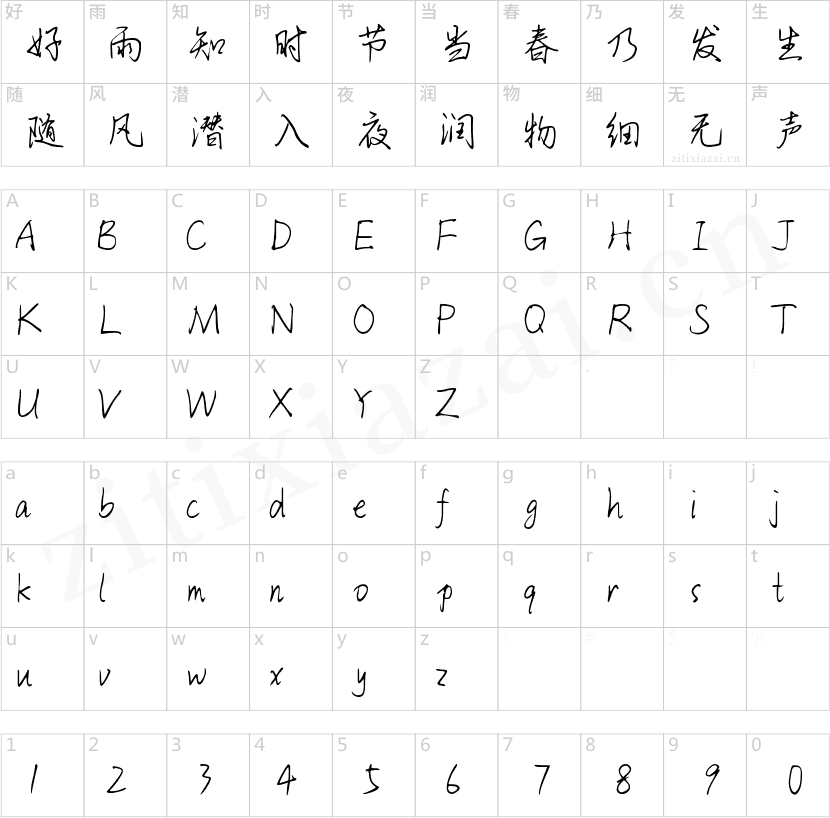
Aa荒城渡
Aa荒城渡字体
Aa荒城渡是一款非常具有艺术性的字体,它的设计灵感来源于对古典艺术的研究,同时又融入了现代字体设计的元素。字形优美,笔画粗细变化自然,给人以大气、典雅的感觉。Aa荒城渡是一款既传统又现代的字体,它的设计充满艺术感,美观大方,实用性也非常强。无论是对于设计师还是对于普通读者来说,都是一种非常不错的字体选择。Aa荒城渡适合用于具有艺术感的场合,比如海报、宣传单张、书籍封面等。由于其字形流畅且具有动态感,也适合用于大量的文本排版,如报纸、杂志等。